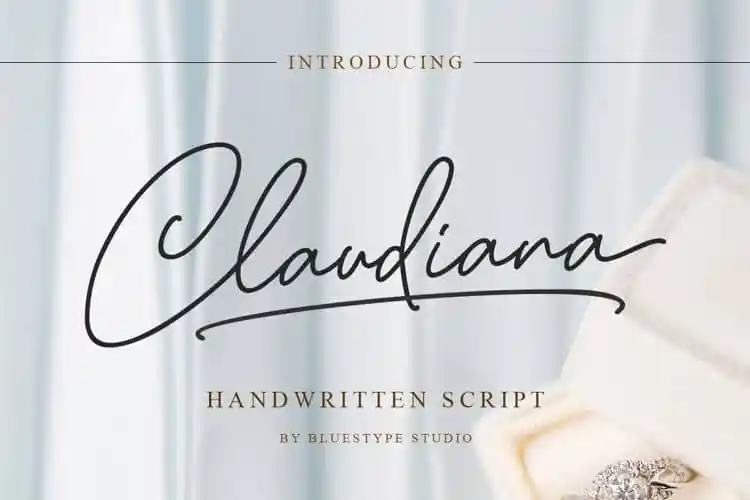
Claudiana Handwritten Font – Fonte Grátis
Claudiana Handwritten Font
A fonte ‘Claudiana Handwritten Font’ é uma opção perfeita para qualquer projeto que precise de uma tipografia agradável e versátil. Essa font foi projetada para combinar perfeitamente com outras letras, permitindo aos designers criar belos traços manuscritos rapidamente e sem esforço. Ideal tanto para o logotipo quanto para cartões de negócios, a ‘Claudiana Handwritten Font’ também é uma ótima escolha para projetos relacionados à celebração, como bodas. Seja na criação de estampas para camisetas ou em designs de livros e revistas, essa font se destaca por sua capacidade de adaptar-se a um amplo espectro de usos. Compreendendo também as necessidades do design fashionista, da produção de texturas úmidas nas etiquetas, das cartas de convite até as marcas de embalagem, a ‘Claudiana Handwritten Font’ tem tudo o que você precisa para transformar seu próximo projeto em algo realmente especial.